タイププロジェクト、TBSホールディングスにコーポレートフォントとブランディングフォントを同時に提供
タイププロジェクト株式会社(東京都練馬区 代表取締役社長 鈴木 功、以下タイププロジェクト)は、株式会社TBSホールディングス(東京都港区赤坂5丁目3番6号以下、TBS)がタイププロジェクトのAXISフィットフォントおよびTP明朝フィットフォントをTBSのコーポレートフォントとして導入したことを発表しました。合わせて、ブランディングフォントとして欧文を新規に開発した、AXIS Fontのカスタマイズ版を採用しました。
■ コーポレートフォント
TBSでは、ブランディング強化の施策として、名刺や社内外の資料、番組テロップ、Webサイト、デジタルサイネージなどに統一感を持たせるため、新しくコーポレートフォントを導入しました。読みやすく洗練されたデザインという視点でAXIS フィットフォントと、TP 明朝フィットフォントから、コーポレートフォントとして最適な数値のフォントが選ばれ、「TBS ゴシック TP」「TBS 明朝 TP」として提供しています。
「TBS ゴシック TP」と「TBS 明朝 TP」は、約3,700人のグループ社員のパソコンにプリインストールされているほか、名刺、局内の看板、営業資料、投資家向け冊子などですでに使用が開始され、フォント選定のコスト削減に役立っています。
同社総合プロモーションセンター兼デザインセンターの松原貴明氏は、「会社としてコーポレートフォントの導入は初めてなのですが、グループ会社を含めた全社員のパソコンにプリインストールされているのは、会社としては非常に大きな変化です。『TBSと名のつくオフィシャルなフォントがあることで、外向きの見え方が統一されていく』など、コーポレートフォントを導入することの意義や、使うことの意味が理解され始めていると感じています」と述べています。
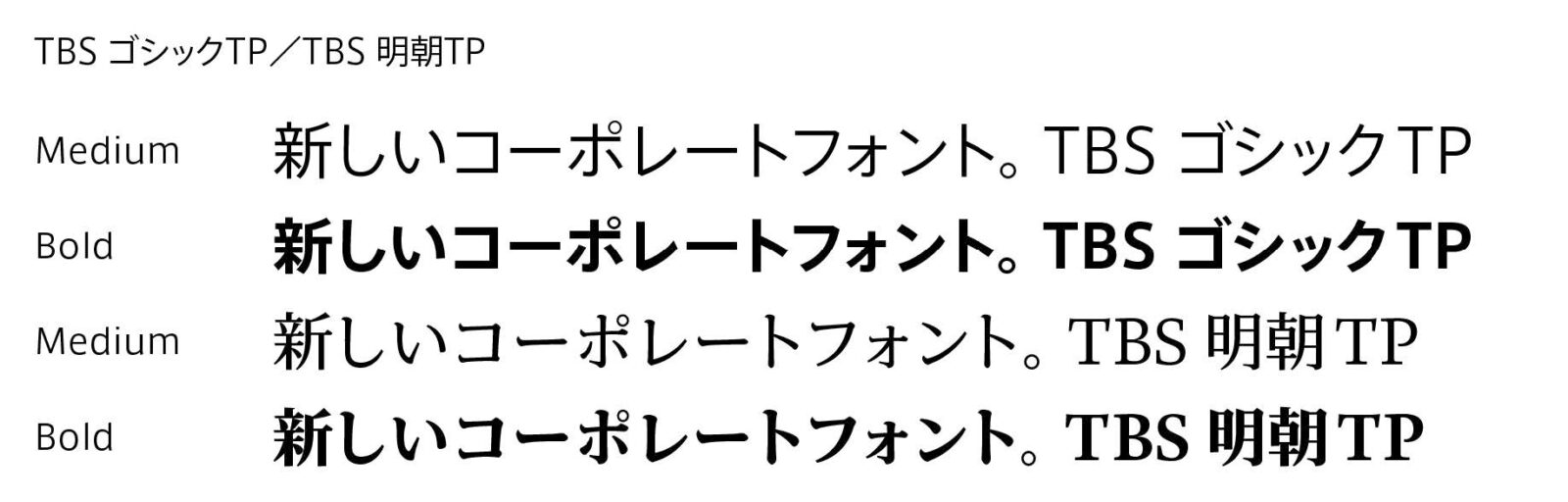
■ ブランディングフォント
TBSグループは、地上波・BS放送、ラジオ放送などグループ会社やサービスごとに異なるデザインのロゴを使用していましたが、それを1つのTBSブランドとして見せるため、オリジナルフォント「TBS Sans TP」を導入しました。タイププロジェクトは、「TBS Sans TP」の欧文部を新たにデザインし、AXIS フィットフォントの和文部と組み合わせて提供しました。
「TBS Sans TP」は、TBSの新ブランドプロミス「最高の“時”で、明日の世界を作る」のコピービジュアルを始め、番宣CMやグループ会社や各サービスのロゴなど、あらゆる場面で使用されています。
「原型となるオリジナルデザインを元に、新たに欧文を開発していただきました。フォントを検討する必要がなくなったことで、とても効率的に進めることができ、誰が担当してもデザインにブレがないので、TBS Sans TP を使える安心感は大きいですね」と、デザインセンターの團野慎太郎氏は述べています。
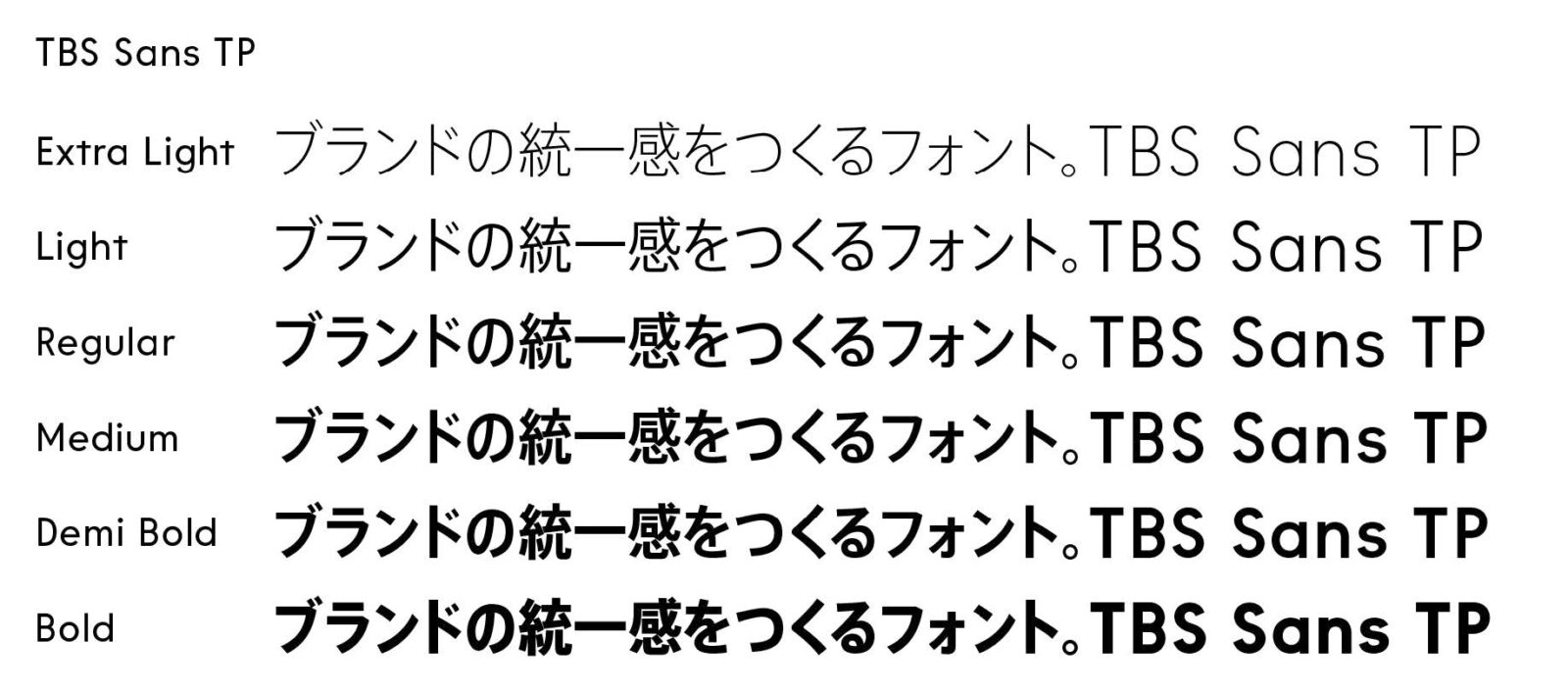
タイププロジェクトでは、企業のメッセージを伝えるための手段としてフォントによるブランディングを提案しています。フィットフォント技術を用いて、既存フォントのウエイトやコントラストを調整したり、他社欧文と組み替えるほか、オリジナルの欧文や仮名を開発するなど、世界有数のグローバル企業にコーポレートフォントを提供しています。
タイププロジェクトの鈴木功は、「広く使いやすいコーポレートフォントと、ブランディングのためのカスタマイズフォントをそれぞれ導入いただくのは、企業ブランディングとして理想の形だと思います。今回、TBSにその両方を提供する機会を得たことをとても嬉しく思っています」と述べています。